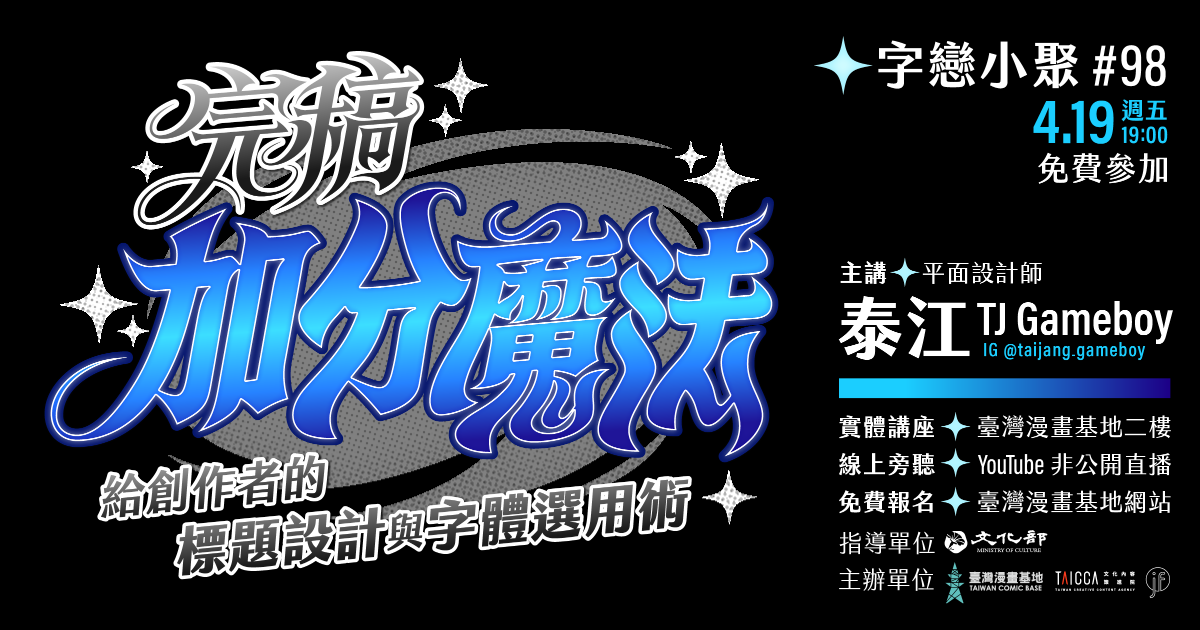
字戀小聚 #98|完稿加分魔法:給創作者的標題設計與字體選用術
泰江 TJ Gameboy 立志做出好看又好玩的設計,擅長風格鮮明又活潑的文字造形。這次江分享如何將腦中的想法落實。
除了泰江 TJ Gameboy 的分享,字型教育與設計團隊 justfont 也將分享既有字型選用指南,幫你建立好用字體偵測器!
如果你常遇到以下狀況,那這場活動就是為你而來!
❓想加點文字讓畫面更完整,但總是覺得差一味
❓想幫自己的作品畫標題,但成果和想像有點不一樣
❓想用字體表現不同的語氣與氛圍,但不知道該怎麼做
❓好不容易找到可愛的字體了,但是用了才發現缺好多字
關於講者
平面設計師|泰江 TJ GAMEBOY
啟發於遊戲、動漫、音樂等流行娛樂,
開始對於創作產生興趣並夢想成為漫畫家,
然而事與願違誤打誤撞變成了平面設計師,
現於字體設計、平面視覺和插畫領域持續耕耘著,
並立志做出好看又好玩的設計作品。